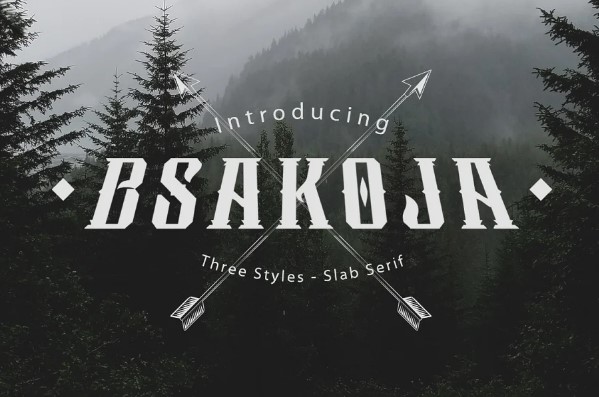
Creativemarket Bsakoja Font
[Creativemarket] Bsakoja Font
Шрифт Slab Serif, поставляется с 3 различными стилями : Обычный, кривой и трафаретный.
Гибкие формы, которые можно применять в винтажном, минималистском или современном стиле.
Изогнутый стиль рекомендуется для вашей цели печати.
В целом, хорошая деталь для цифровой или любой печати, как на тройники, наклейки, плакаты, рекламные щиты или одежду.
Специально для вашего заголовка.